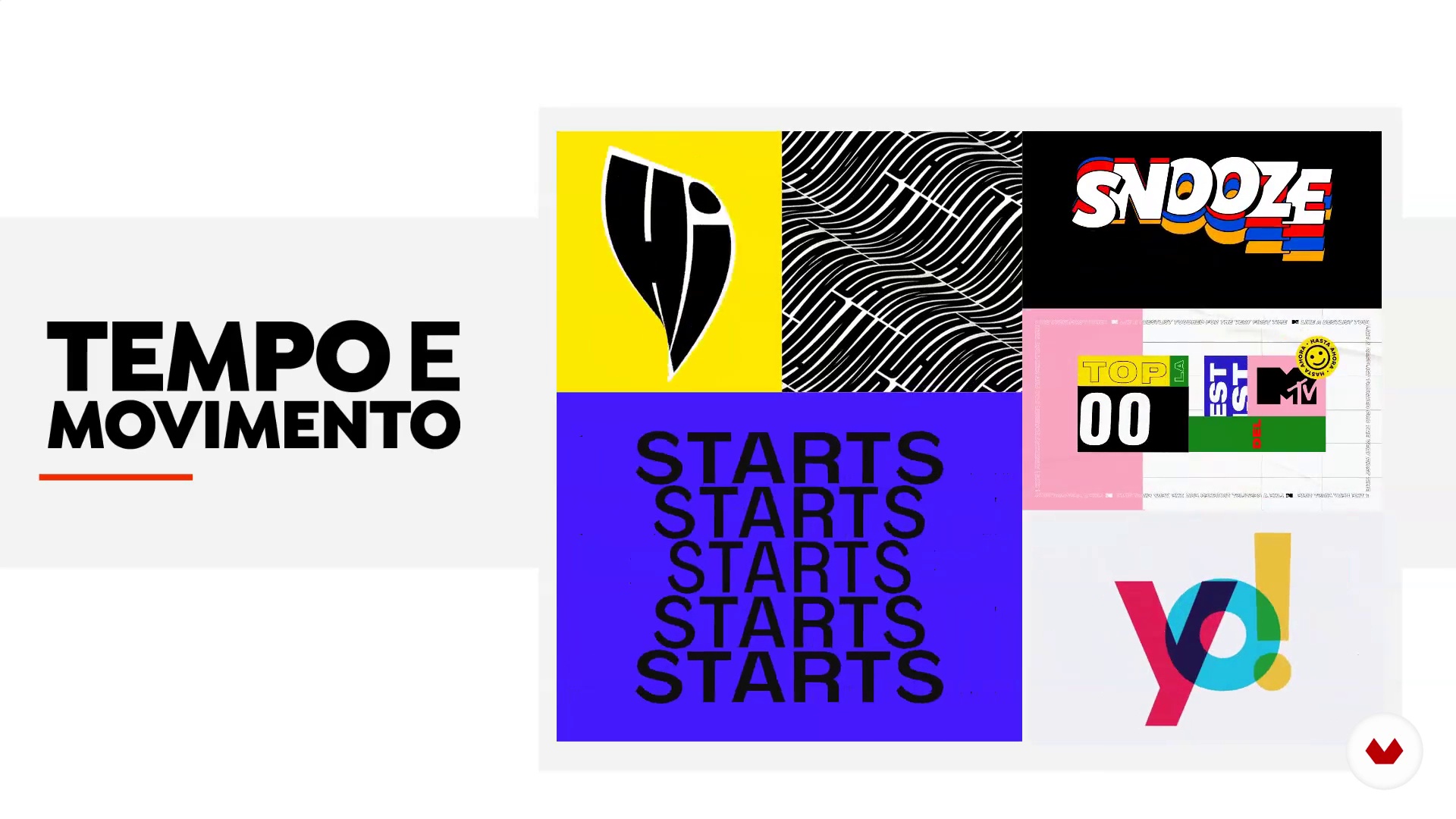
Tipografia in motion design
A proposito della videolezione: Tipografia in motion design
“Prima di iniziare le nostre animazioni, parlerò un po 'della tipografia nel motion design.”
In questa videolezione, Érico Santana tratta il tema Tipografia in motion design, che fa parte del corso online di Domestika Animazione tipografica con After Effects. Scopri le tecniche creative del motion design e crea tipografie animate e originali.
“In questa lezione. parlerò un po' di tipografia per il motore di zâmbito. La tipografia è l'arte e la tecnica di comporre titoli. cioè fonti e etichette. dando una struttura e una forma alle parole per comunicare ciò che desideriamo. Nel Monster Design. è certo che ti imbatterai in animazione tipografica. ti presenterò alcuni punti importanti per lavorare autonomamente con la tipografia. come leggibilità. impaginazione. tipo di carattere. tempo e movimento. Andiamo? Tipografia per il Motion Design. Che cos'è la tipografia. La tipografia è l'arte e la tecnica di organizzare i tipi. che sono ...”